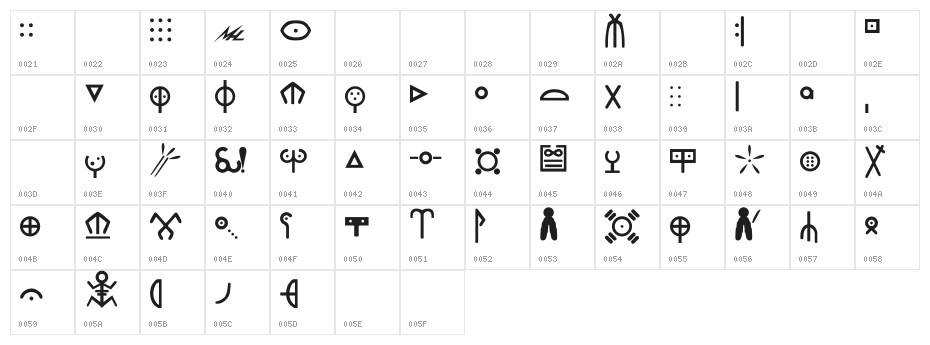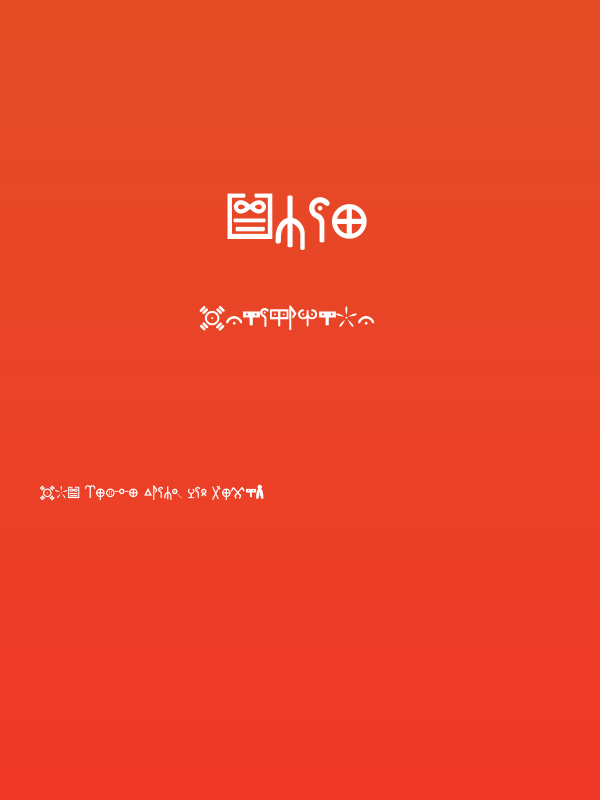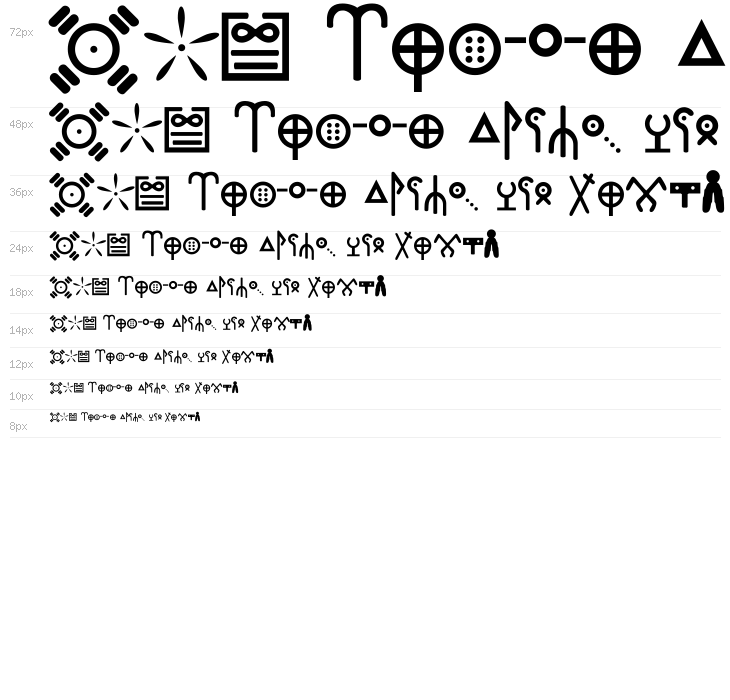
Ewok Font
| Categorie | Images & Symbols |
| Stile generale | Decorative, Futuristic, Playful |
| Caso d'uso | Logos, Headlines, Posters, Themed graphics |
| Progetti proposti | Fantasy or sci-fi themed posters, game interfaces, movie titles, alien language representations, creative branding. |